手迹(笔迹),指各个人所写的字所特有的形体特点。不同的人必然会形成不同的笔迹,它反映了一个人生理、心理因素甚至身体外表。笔迹鉴定和笔相学等都是有关笔迹的学问。
在中国民间常有“字如其人”的说法,一方面通过字体,笔迹,能够看出一个人的心态和性格,另一方面从字也能看出一个人的学识和修养。
人类的大脑与双手是息息相关的,手部活动能通过许多方式反映人的内心世界的活动状况。学者们普遍认为,与其说手在写,不如说是大脑在写指尖的各种运动,只不过是人内心世界在无意识下的一种不加修饰的流露,手写字体时的每一笔每一画都能反映出每个书写人独特的个性。所以说,通过笔迹可以挖掘一个人的内心世界。
拿王羲之的字来说,清风出袖,遒劲媚逸,萧散平和。他的字与品性直接相关:其一身正气,清廉做官,关爱百姓,乐于助人。所以,都说“字如其人”,笔迹确实能展示写字人的个性。
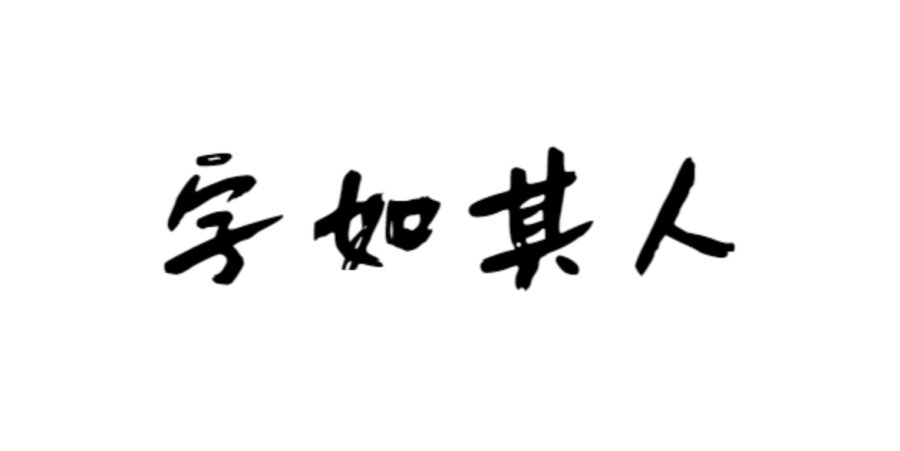
笔迹与性格关系:
1、字小:观察力好,注意力集中。适合脑力劳动,想像力丰富。但稍嫌神经质,不善做体力劳动,且非常在意别人对自己的看法。
2、笔划圆滑:温和,亲切,顺从。性情随和,适应性强。
3、偏瘦长:极富创造力和想象力,不拘小节。
4、字间紧凑:吝啬,做事谨慎。
5、字体倾斜:字体左倾者情感压抑,小心谨慎,好内省,关注自己,对周围环境反应冷漠;字体右倾者积极进取,能动性强,不怕困难,独立自主,待人友好,性情开朗,但容易受他人影响。
6、正方形:品行端正、为人正直,责任心强。尊重传统,原则性强,自我控制能力强,情感不容易外露。
7、扁形:固执己见,爱钻牛角尖,做事认真、负责、行事有条理,有计划,但有时刻板僵化,缺乏弹性。
8、中等大小:写中等字的人注重实践,对外界环境适应能力强的,工作中与人相处友好的。
9、有棱有角:说明观点和意图坚定,不过喜欢加剧冲突,
10、笔画不匀称:喜欢破坏,脾气暴躁,容易因琐碎小事就会伤心。
11、下笔轻重:笔画很重的人敏感,容易计较小事;笔画过轻的人则不自信,喜欢自责。
12、大字:性情直爽,明朗,充满自信,外向,毫不犹豫地坚持自我。
笔迹字体总归是后天形成的,反映出来的特性也会有例外。不过“字如其人”,确实不假,毕竟字迹能反映一个人的出身交际、聪明才智,思想性格。